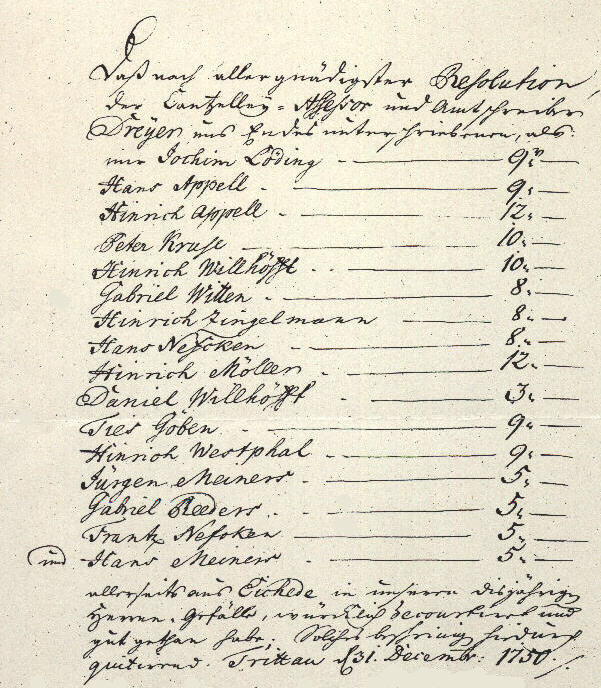
Leseübung : eine Amtsakte von 1750 mit Unterschriften
Official document, signed by farmers, 1750
Dies ist die Widergabe einer alten Amtsakte von 1750. Es geht darum, daß der Amtsschreiber die Pacht (genannt "Herren - Gefälle") von den Bauern einkassieren mußte und die Befugnis hatte, in Härtefällen einen geringeren Betrag zu fordern, als sonst.
Für die Abrechnung wurden die geforderten Beträge von den Bauern per Unterschrift bestätigt.
Der Text der Quittung ist in Kanzleischrift geschrieben, die Namen der Bauern in lateinischer Schrift, die dem Amtsschreiber ungewohnt ist, denn einzelne Buchstaben sind trotzdem in der gewohnten Kanzleischrift, nämlich : "d" in Löding und in Reeders sowie das "s" in Kruse.
Diese Seite mit dem Quittungstext ist eine gute Leseübung für Anfänger. Die untere Hälfte mit den Unterschriften ist sehr schwer zu lesen, ist abgetrennt und auf dieser Seite erkärt.
"Daß nach allergnädigster Resolution der Cantzelley-Assessor und Amtschreiber Dreyer uns Endes unterschriebenen, als
mir Jochim Löding, Hans Appell, Hinrich Appell, Peter Kruse, Hinrich Willhöfft, Gabriel Witten, Hinrich Zingelmann, Hans Nefcken, Hinrich Möller, Daniel Willhöfft, Ties Göben, Hinrich Westphal, Jürgen Meiners, Gabriel Reeders, Frantz Nefcken, und Hans Meiners
allerseits aus Eichede in unserem disjährigen
Herren - Gefälle, würklich decourtiret (?) und
gut gethan habe; Solches bescheinigen hirdurch
quitierend Trittau den 31. Decembr. 1750 .... (es folgen die Unterschriften)
Die untere Hälfte mit den Unterschriften ist sehr schwer zu lesen und auf dieser Seite erkärt.